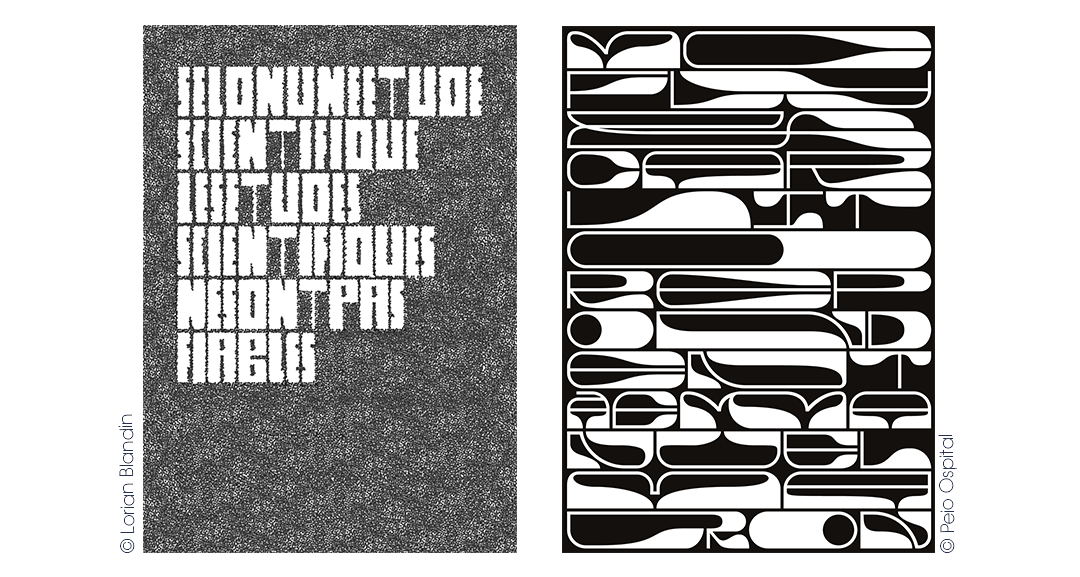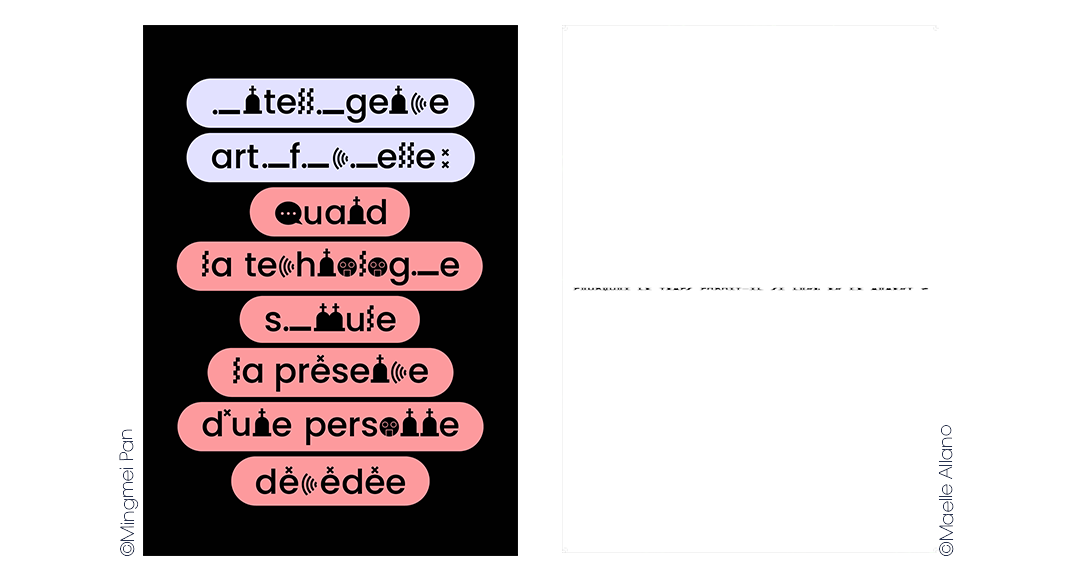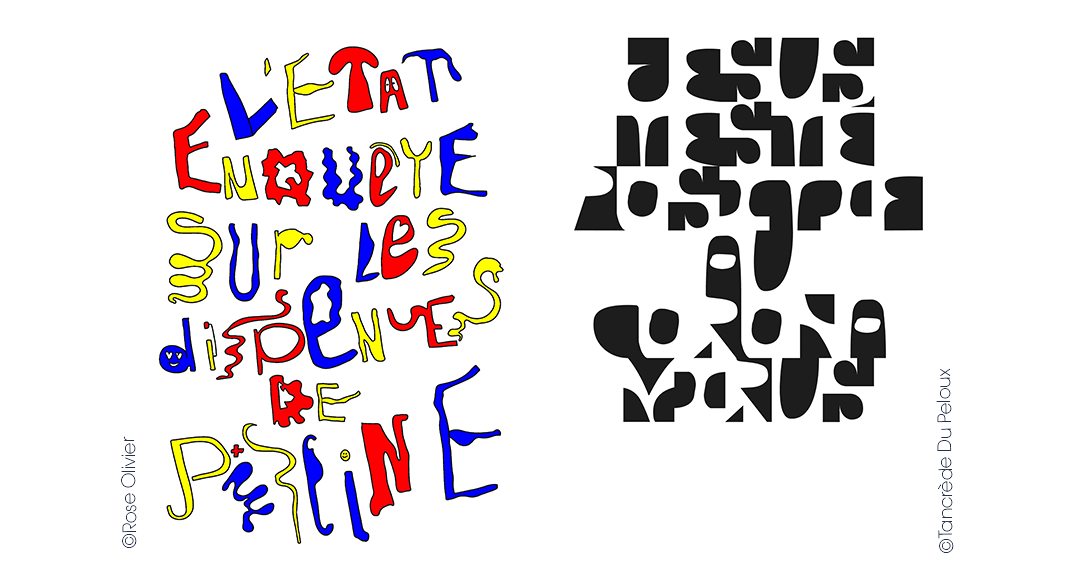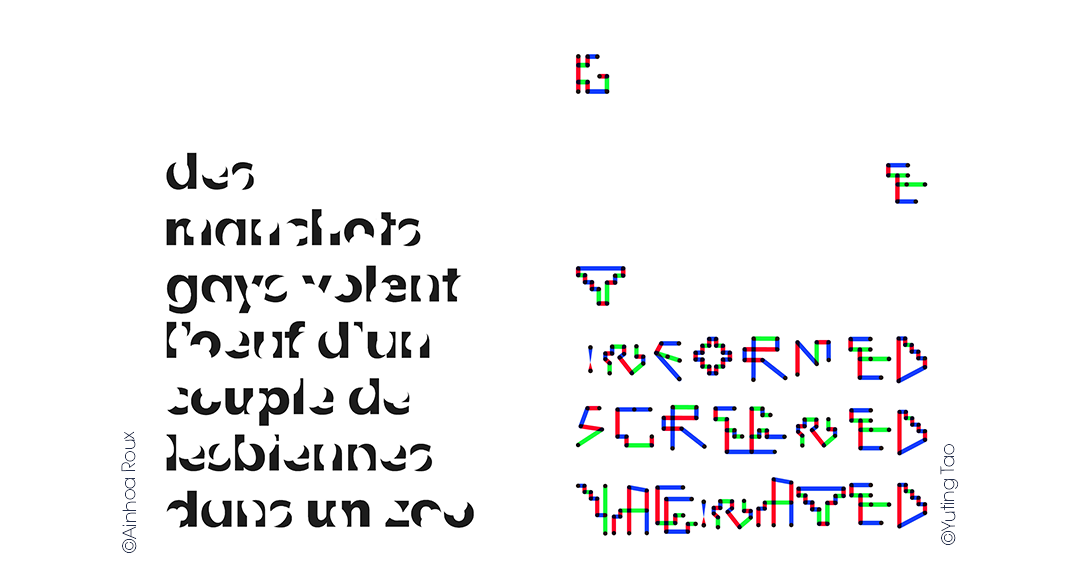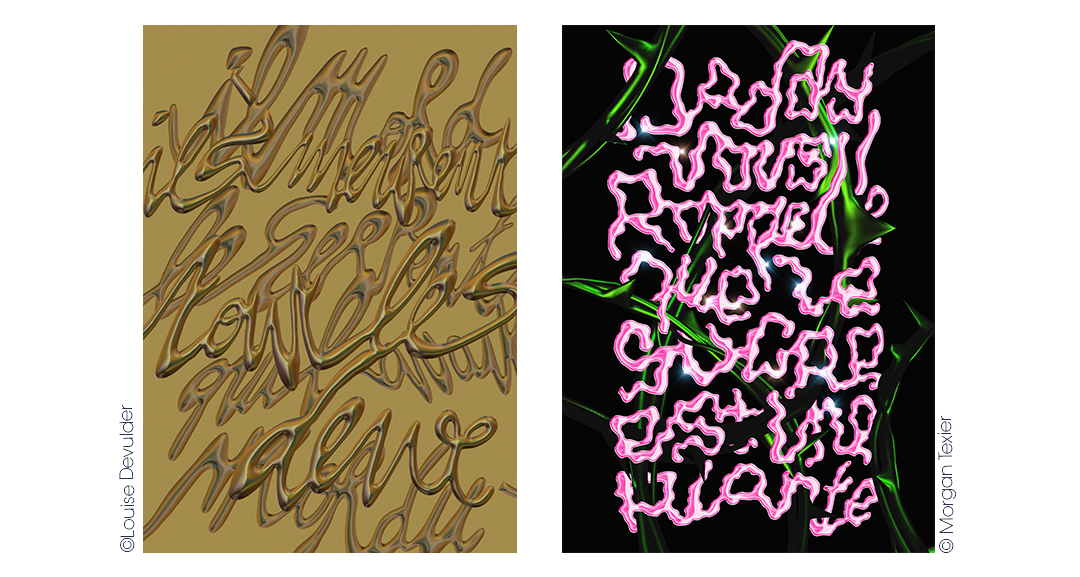
Workshop Typographie avec Loris Pernoux, Dessinateur de caractères
Du 22 au 26 février, les étudiants en 2e année de Mastère Design Graphique à l’ECV Nantes ont participé à un workshop dédié à la Typographie avec Loris Pernoux, Designer Graphique, Dessinateur de Caractères et co-pilote du collectif Brest Brest Brest.
Toute la semaine, Loris Pernoux a apporté son expertise pour permettre à nos étudiants d’expérimenter la création typographique de manière ludique sur la thématique “Clair de loin, mais loin d’être clair.”
Le brief était le suivant :
Entre déclarations politiques incohérentes ou faits divers improbables, l’absurde s’invite parfois dans les gros titres. Comme base de travail, chaque étudiant devra chercher un extrait d’article, une phrase, un titre d’actualité à faire résonner avec son design et jouer avec son message. Il s’agit de travailler sur la frontière entre la clarté et l’abstraction d’un dessin typographique. Chercher l’illisibilité parfaite, en trouvant le juste équilibre pour que le message mis en forme soit au minimum du compréhensible.
Nos étudiants ont pu en fin de semaine mettre en place une véritable salle d’exposition dans laquelle ont pouvait retrouver l’ensemble de leurs projets sous forme d’affiches typographiques.
Ci-dessous les jolis rendus qui ont découlé de cette semaine riche en créativité.
©Loriane Blandin – « Selon une étude scientifique, les études scientifiques ne sont pas fiables »
©Peio Ospital – « McFly & Carlito répondent à Emmanuel Macron »
©Louise Devulder – « Il mord le serpent qui l’avait mordu, ils meurent tous les deux. »
©Morgane Texier – « Daddy vous rappelle que le sucre est une plante. »
©Mingmei Pan – « Intelligence artificielle : quand la technologie simule la présence d’une personnes décédée. »
©Maelle Allano – « Pourquoi le temps paraît-il si long en ce moment ? »
©Rose Olivier – « L’état enquête sur les dispenses de piscines. »
©Tancrède Du Peloux – « Jesus testé positif au Coronavirus. »
©Ainhoa Roux – « Des manchots days volent l’oeuf d’un couple de lesbiennes dans un zoo. »
©Yuting Tao – « Get informed. Get screened. Get vaccinated. »